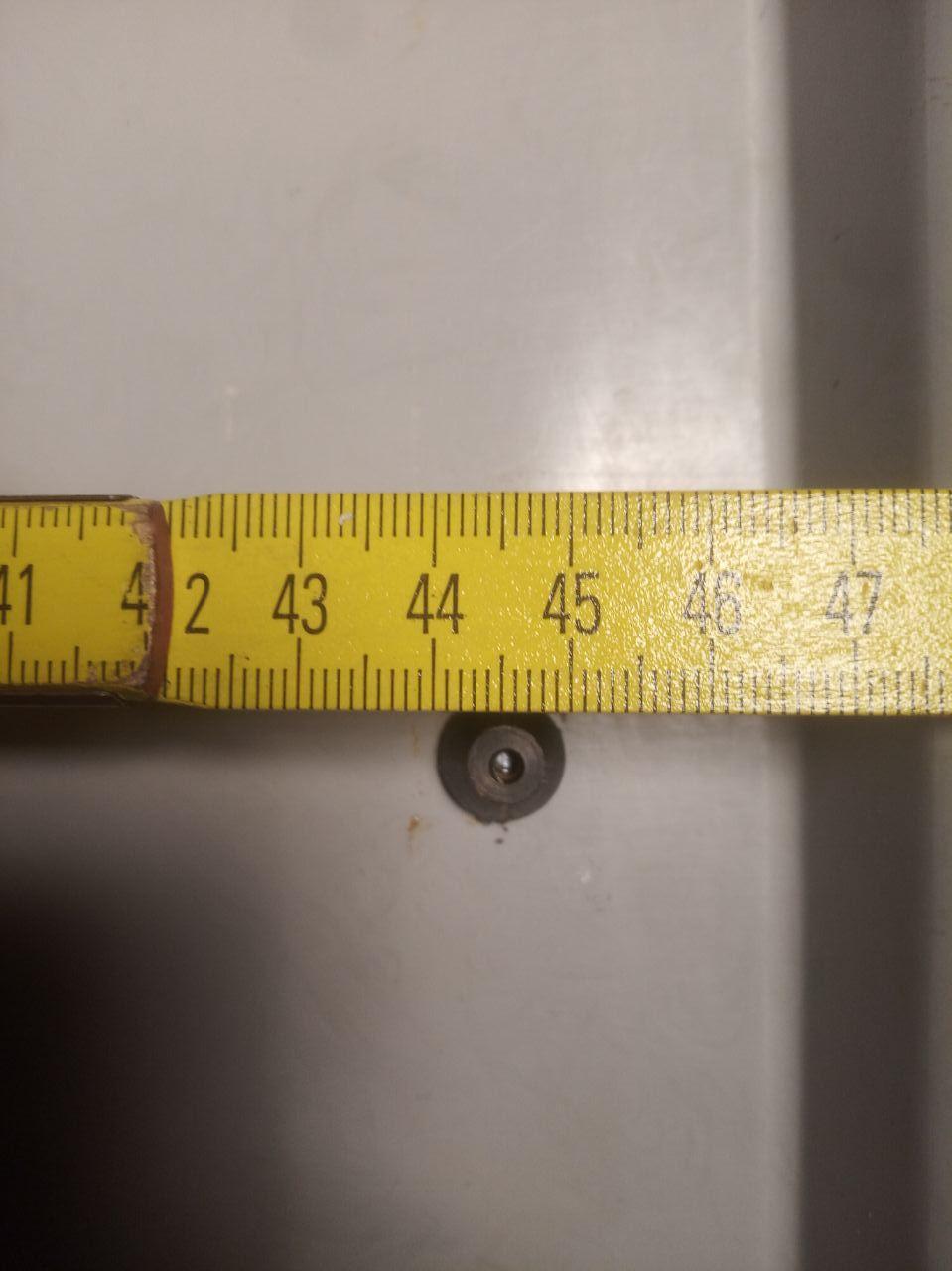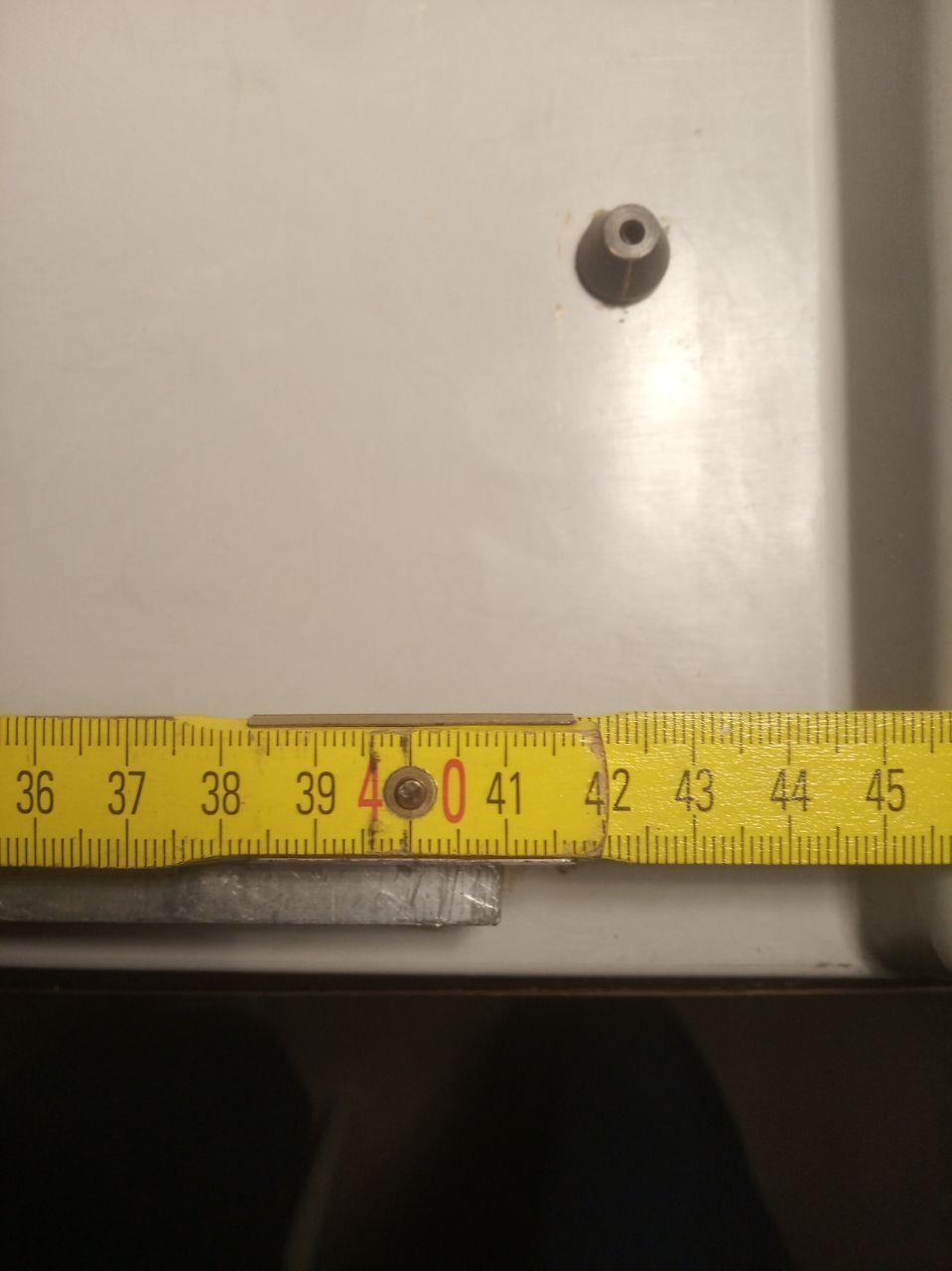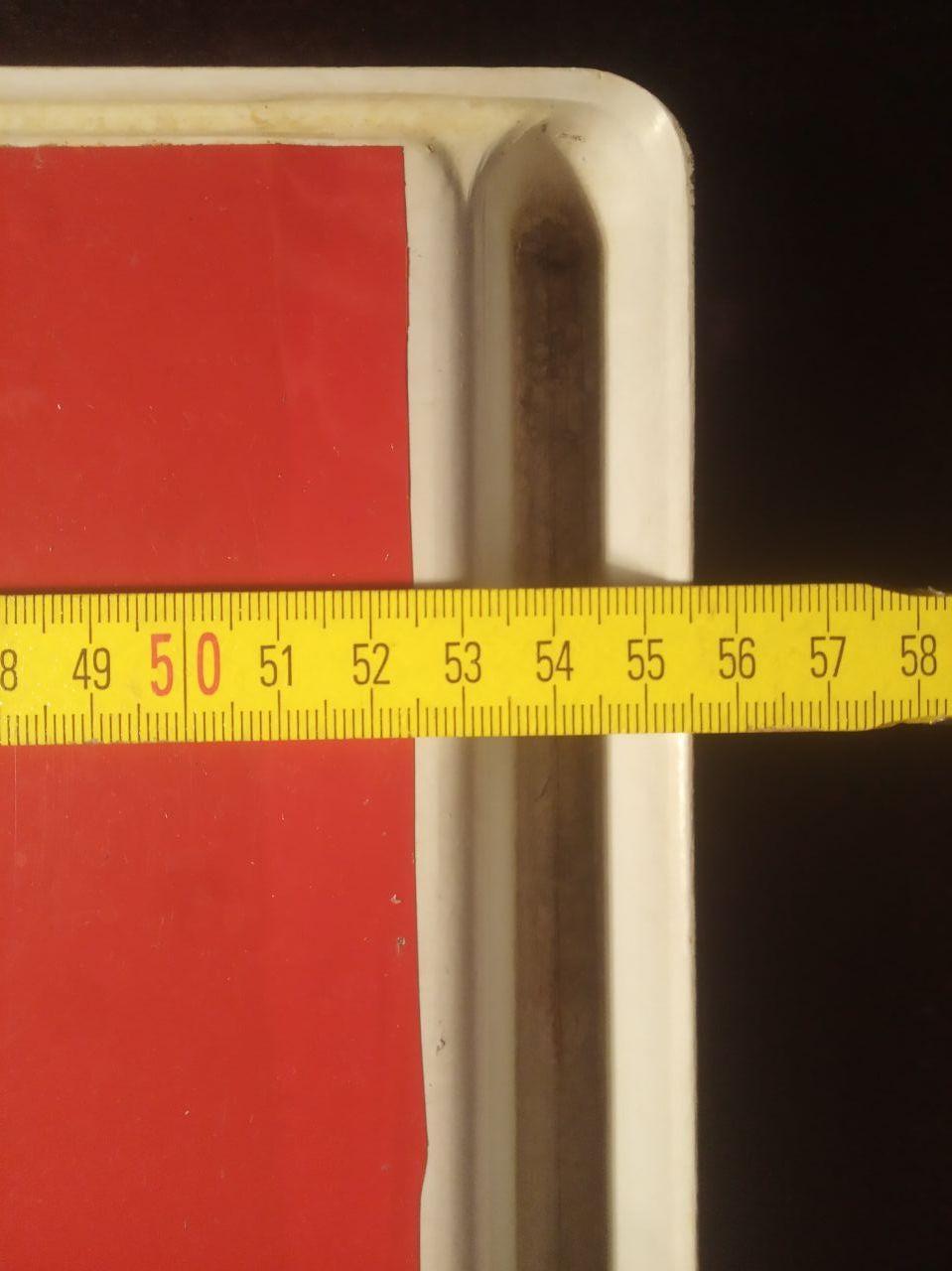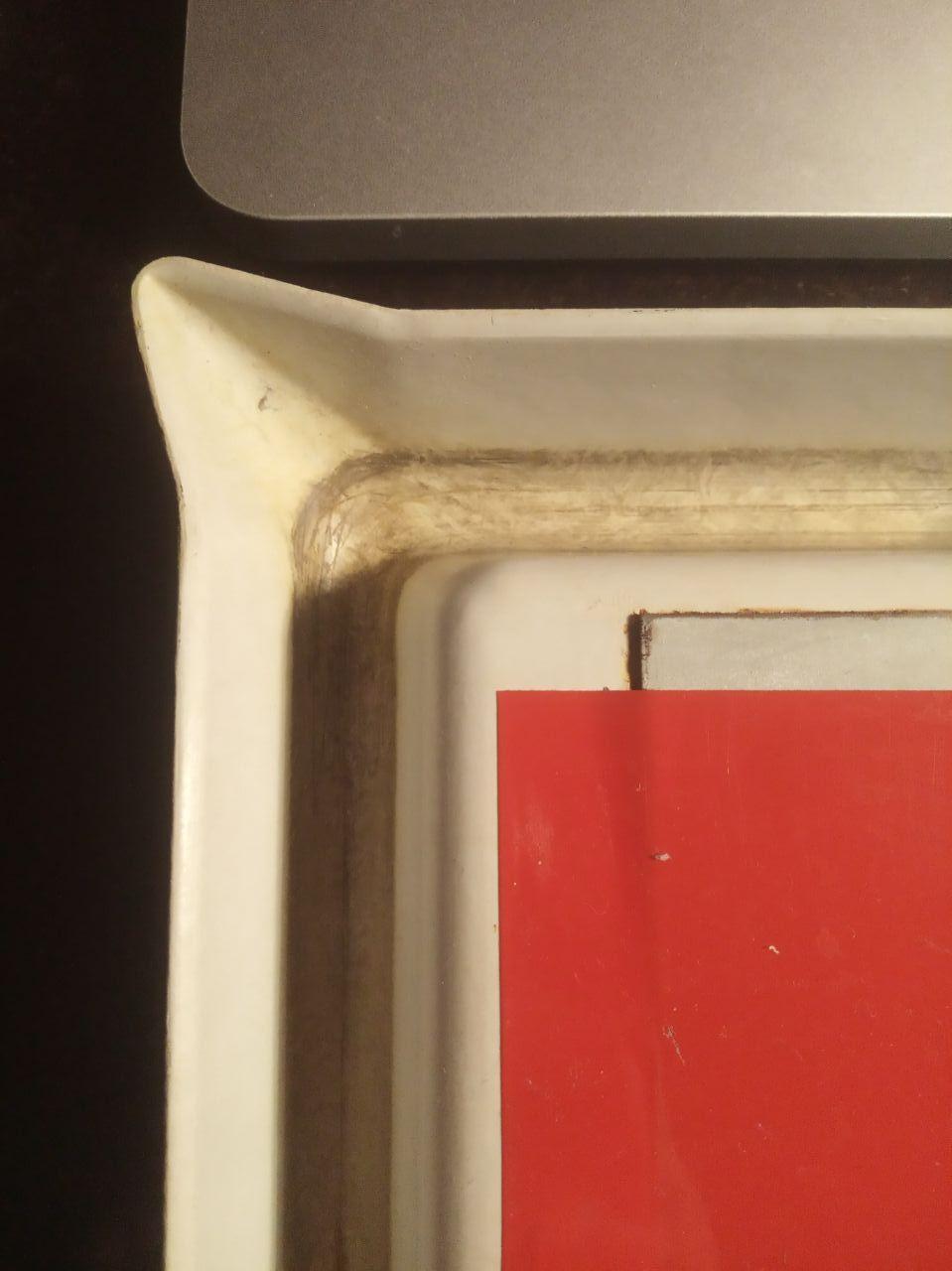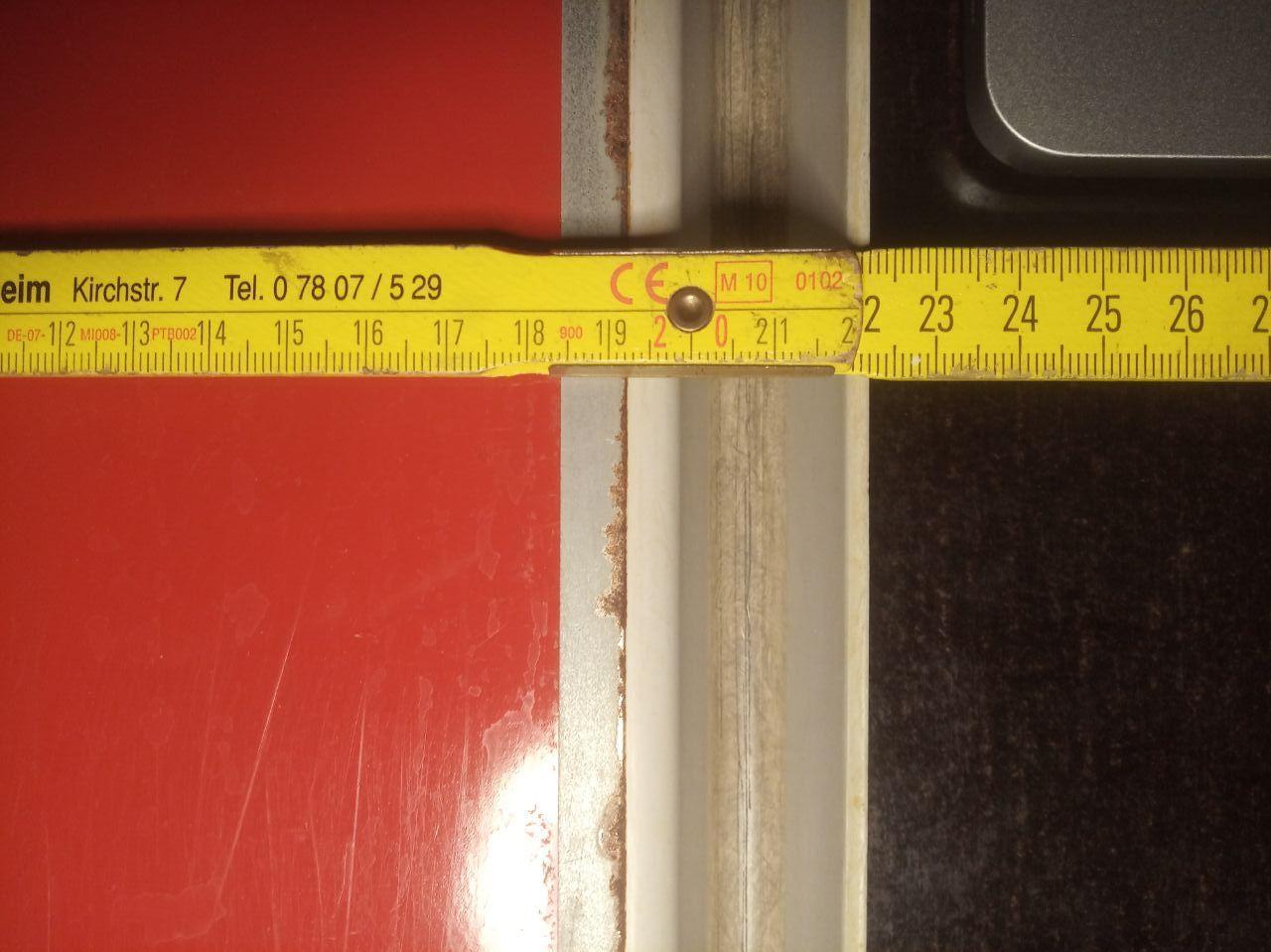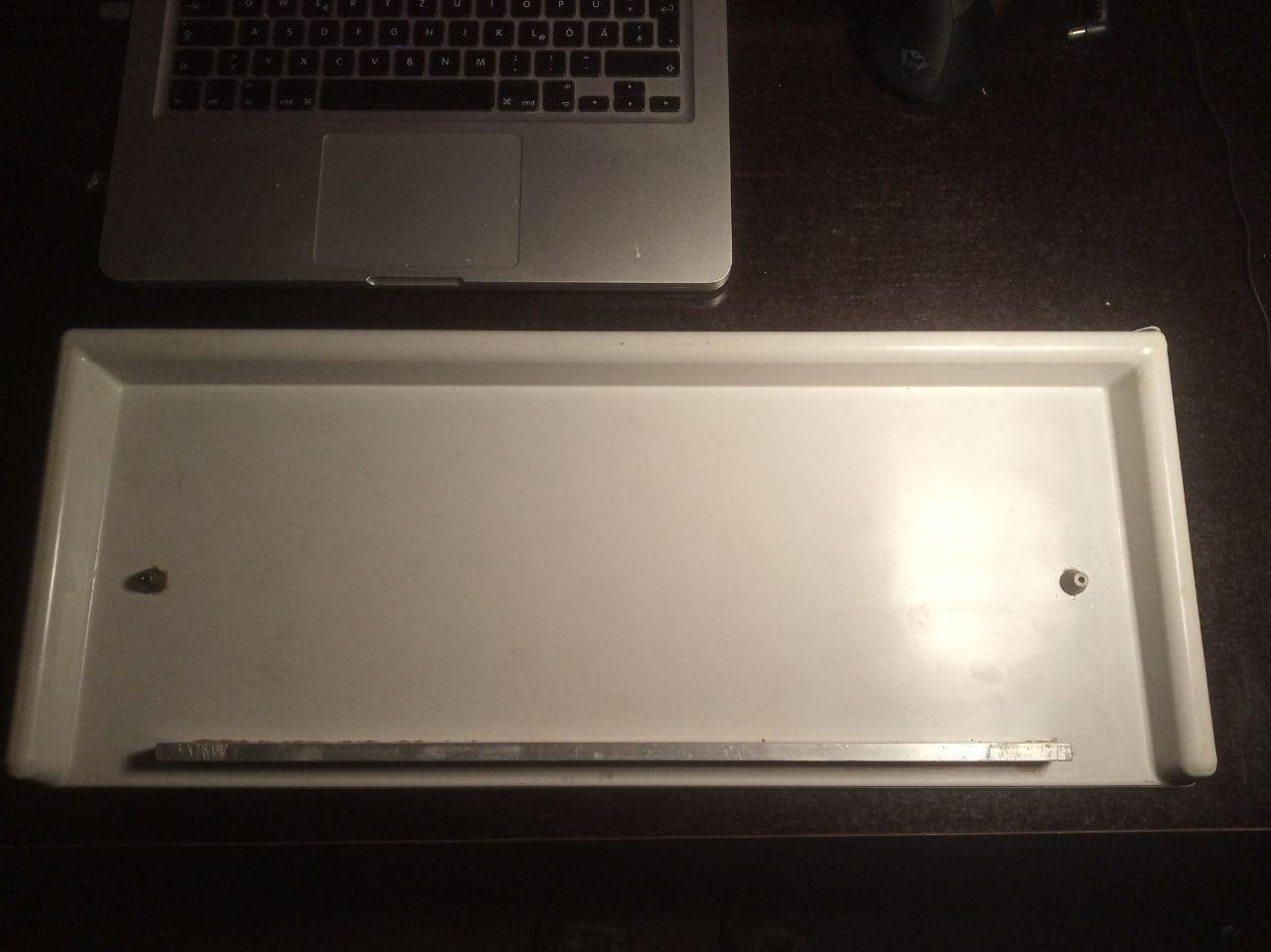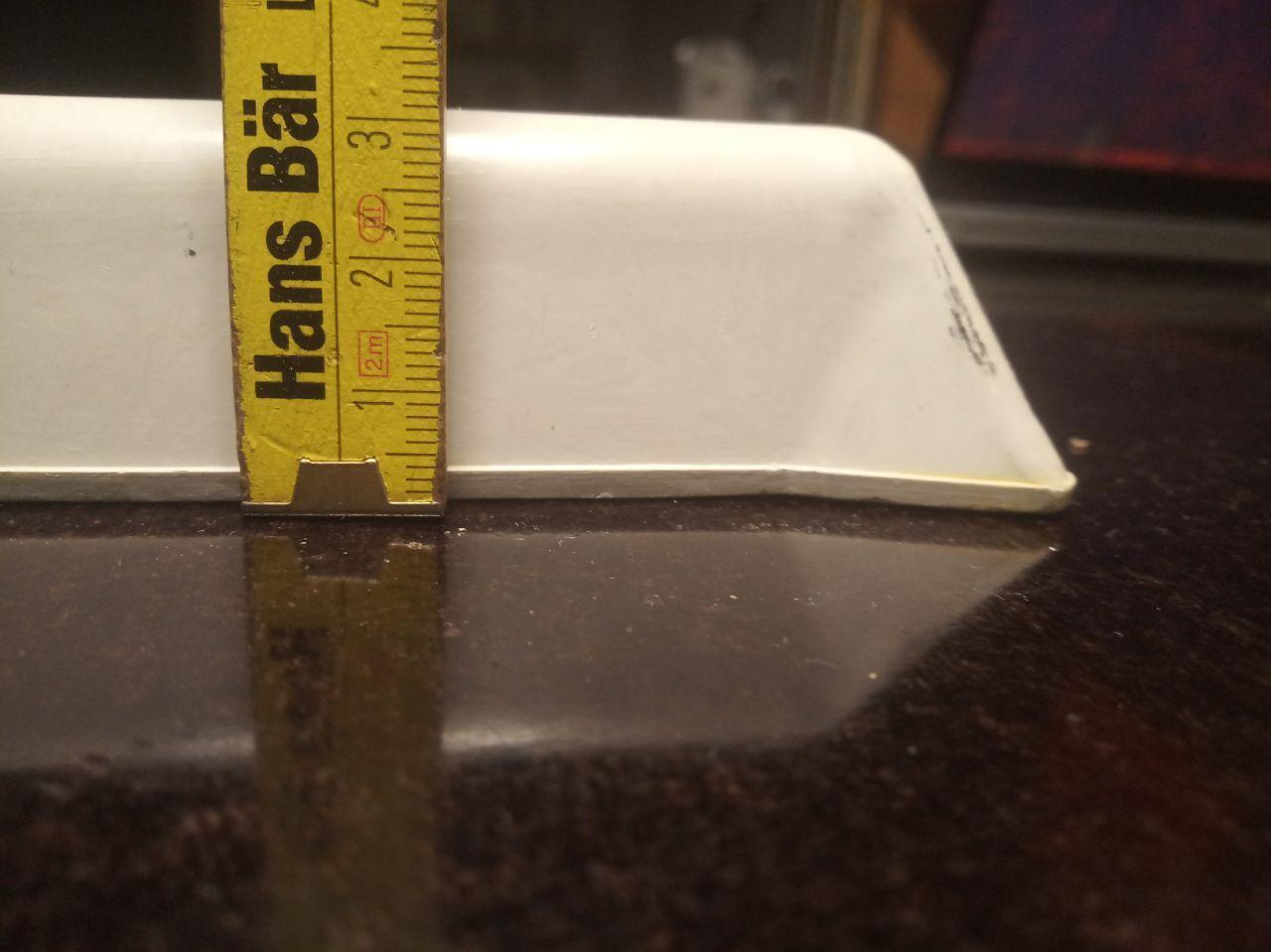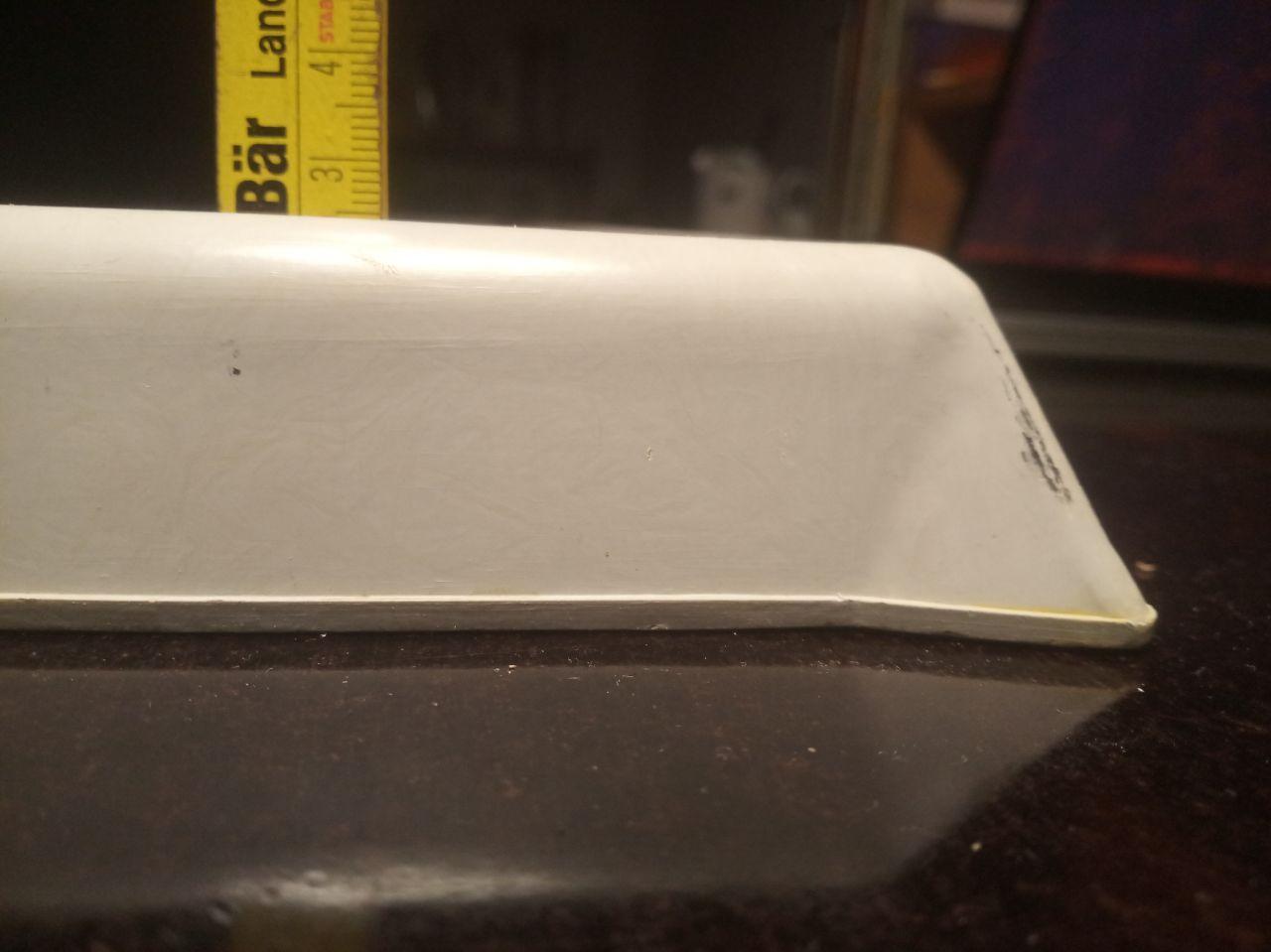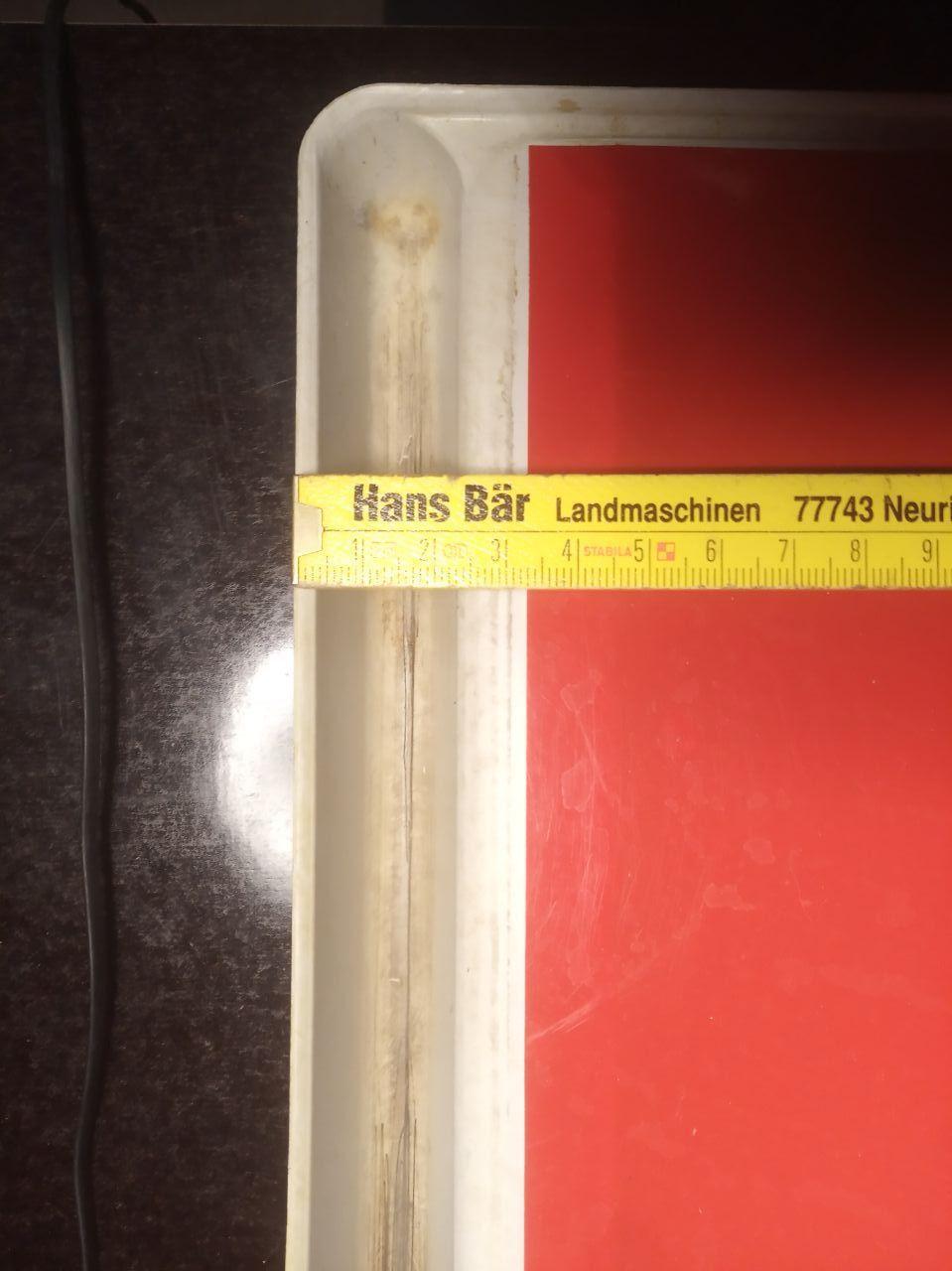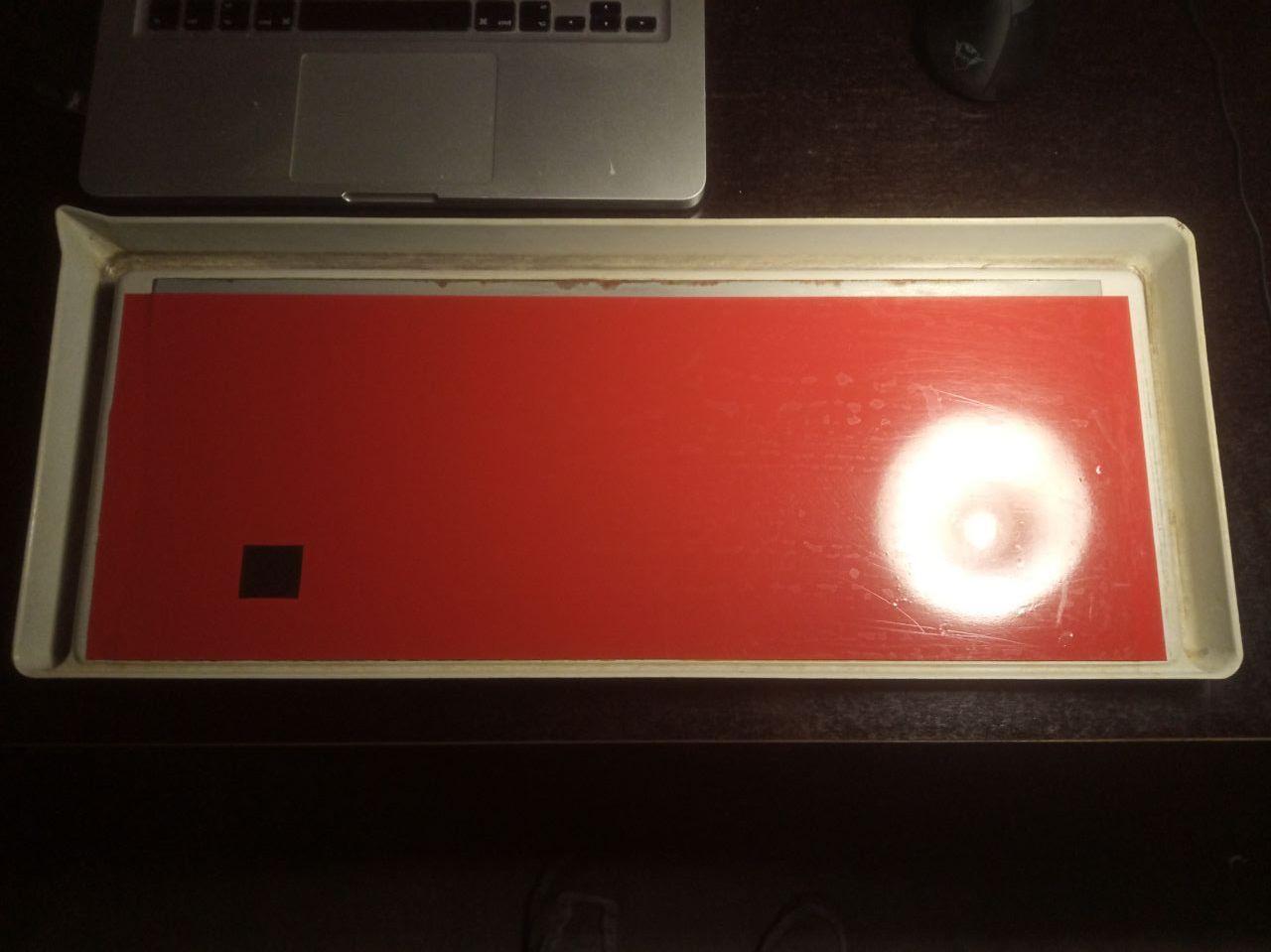
Berthold Staromat, wer erinnert sich?
Hallo, heute mal eine rein technische Frage. Trotz stundenlangem rumgoogeln ist es mir nicht gelungen, heraus zu finden, was das Teil wiegen könnte. Hat da jemand noch irgendeine Erinnerung?
Also, Brett, Säule, Belichtungskopf und der Kreuzschienentisch für Fotopapier? 20kg? Mehr oder weniger? Irgendjemand noch technische Unterlagen in der Schublade?
Info für die Interessierten: Typorama in der Schweiz hat einen Flyer gefunden! Das Teil wiegt schlappe 65 KG nackig, mit allem drum und dran verpackt 75 KG.
So, das Teil ist inzwischen in Mainz angekommen. Muss jetzt teilweise entrostet werden. Falls Interesse besteht, mache ich mal ein paar Detailaufnahmen, im Internet ist ja wenig zu dem Gerät zu finden. Schriftstäbe sind etwa 90 dabei gewesen, in sehr gutem Zustand.
Moin, falls von Interesse, hier ein Auszug aus „Berthold Gesamt-Programm“ von 1979 [129.1(20)279KP].
Was willst du wissen? Ich habe zwar nur einen Starsettograph (die etwas weniger komfortable Ausführung), aber die Arbeitsweise ist identisch. Habe auch jede Menge Schriftscheiben, teils selbstgemacht (Negativ zwischen Plexistreifen). Habe auch Verzerrungsoptik …
Du brauchst dann schon eine Dunkelkammer, weil ja auf lichtempfindliches Material belichtet wird. Auf dem Foto fehlt die Wanne, auf die der Filmstreifen geklebt wird
Du brauchst dann schon eine Dunkelkammer, weil ja auf lichtempfindliches Material belichtet wird.
Das ist klar. Habe damit in den 70igern/8oigern selbst gearbeitet. 86 startete die Agentur, in der ich arbeitete, mit Pagemaker.
Was mich jetzt bei der Beschäftigung mit dem Thema Staromat bzw. fotografischem Titelsatz etwas verwundert, ist wie stiefmütterlich das Thema Fotosatz als auch nur kurze Intermezzo (knapp 30 Jahre) zwischen Bleisatz und DTP-Durchbruch eigentlich behandelt wird.
Zum Staromat findet man kaum etwas im WWW. Kaum Datenblätter, schon gar keine Bedienungsanleitungen oder technische Literatur für den Kundendienst. Für die Diatype und die folgenden Systeme ist da schon mehr zu finden.
Wenn ich mir alte Ausgaben der damalig führenden Typozeitschrift U&Lc anschaue, hatte der Titelsatz mit fotografischen Negativen einen enormen Einfluß auf die typografische Gestaltung. Fontmischungen, Größenmischungen, Unterschneidungen bis hin zu Überlagerungen, weg mit Zeilenabständen und und … vieles wurde plötzlich möglich. Von daher ist dieser Umbruch ein hochinteressantes Kapitel in der typografischer Gestaltung.
Was mich jetzt bei der Beschäftigung mit dem Thema Staromat bzw. fotografischem Titelsatz etwas verwundert, ist wie stiefmütterlich das Thema Fotosatz als auch nur kurze Intermezzo (knapp 30 Jahre) zwischen Bleisatz und DTP-Durchbruch eigentlich behandelt wird.
Zum Staromat findet man kaum etwas im WWW.
Ich weiß nicht, ob das ein Maßstab ist. Da fehlt einfach die Nachfrage. Gilt für tausende andere Spezialgeräte sicherlich auch.
In unserer Museumsführung in Weimar ist der Fotosatz mit Staromat/Diatype und Co. jedenfalls ein fester und wichtiger Bestandteil, gerade weil es in der Bevölkerung eher unbekannt ist und gerade weil es eine Brückentechnologie ist, die viel über die Unterschiede zwischen Blei- und Digitalsatz erklärt.
P.S. Die Staromat-Wanne müsste man wirklich mal wieder auflegen (3D-Druck?). Die fehlt als bewegliches Teil natürlich als erstes.
Hallo, merke schon, da tut sich was zum Thema Fotosatz.
Habe auch noch ein Titelsaz-Gerät hier stehen. (degrafot 100). Wurde ca. 1970 von uns erworben. Hiermit konnte man auch SW-Fotos vom Negativ belichten. Alles musste, wie bekannt in der Dunkelkammer hergestellt werden. Leider habe ich über dieses Gerät keine weiteren Unterlagen.
Ich habe aus dem Nachlaß von Brigitte und Hans Peter Willberg seinerzeit die Staromat-Typenplattensammlung übernommen. Es dürften so 200 bis 300 Scheiben sein (die zusammen seinerzeit 50.000 Mark gekostet haben, oder habe ich mich verrechnet?). Größe: 75 × 5 cm, Berthold-Originale. Es gab wohl zu vielen Schriften Staromat-Varianten, die sonst nicht zu finden sind. Die Typenplatten stecken in einer mäßig geeigneten Holzkiste, siehe Bilder. Wenn sie in Ehren gehalten und benützt würden, besonders zu musealen oder Lehr-Zwecken, gebe ich sie gerne an Selbstabholer ab. Ich finde, sie sollten zusammenbleiben.
Ich habe aus dem Nachlaß von Brigitte und Hans Peter Willberg seinerzeit die Staromat-Typenplattensammlung übernommen.
Habe mir einen Staromat angeschafft und ergänzend würde ich noch anmerken dass die Wanne eine umlaufende Rinne hat und diese Rinne hat eine Nase zum ausgiessen der Flüssigkeiten...
Kannst du uns mal ein Foto der Wanne zeigen, wo man die Details sieht?
Exakt, so sah die Wanne aus ... und die beiden Nupsies unten sorgten dafür, dass sie in die Führung vom Schlitten passten.